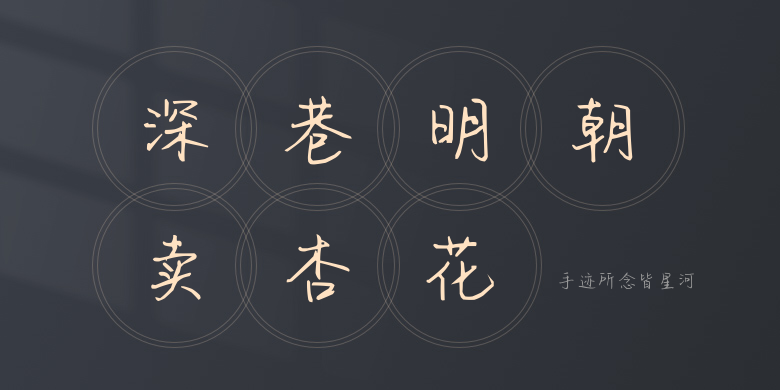
手迹所念皆星河
手迹所念皆星河,这款字体结构工整、笔画清晰,兼顾美观与易读性,适用于标题、正文、海报、包装、LOGO 等多种场景。字形优雅稳定,风格百搭耐看,适配日常排版与创意设计,让文字呈现更舒适、更具质感。手迹所念皆星河一笔一画,皆是细节,以均衡的比例、流畅的线条打造舒适视觉体验,字形端正大气,风格简约现代。无论是商业设计、品牌宣传还是日常排版,都能轻松驾驭,让文字更有格调与力量。手迹所念皆星河字体下载。